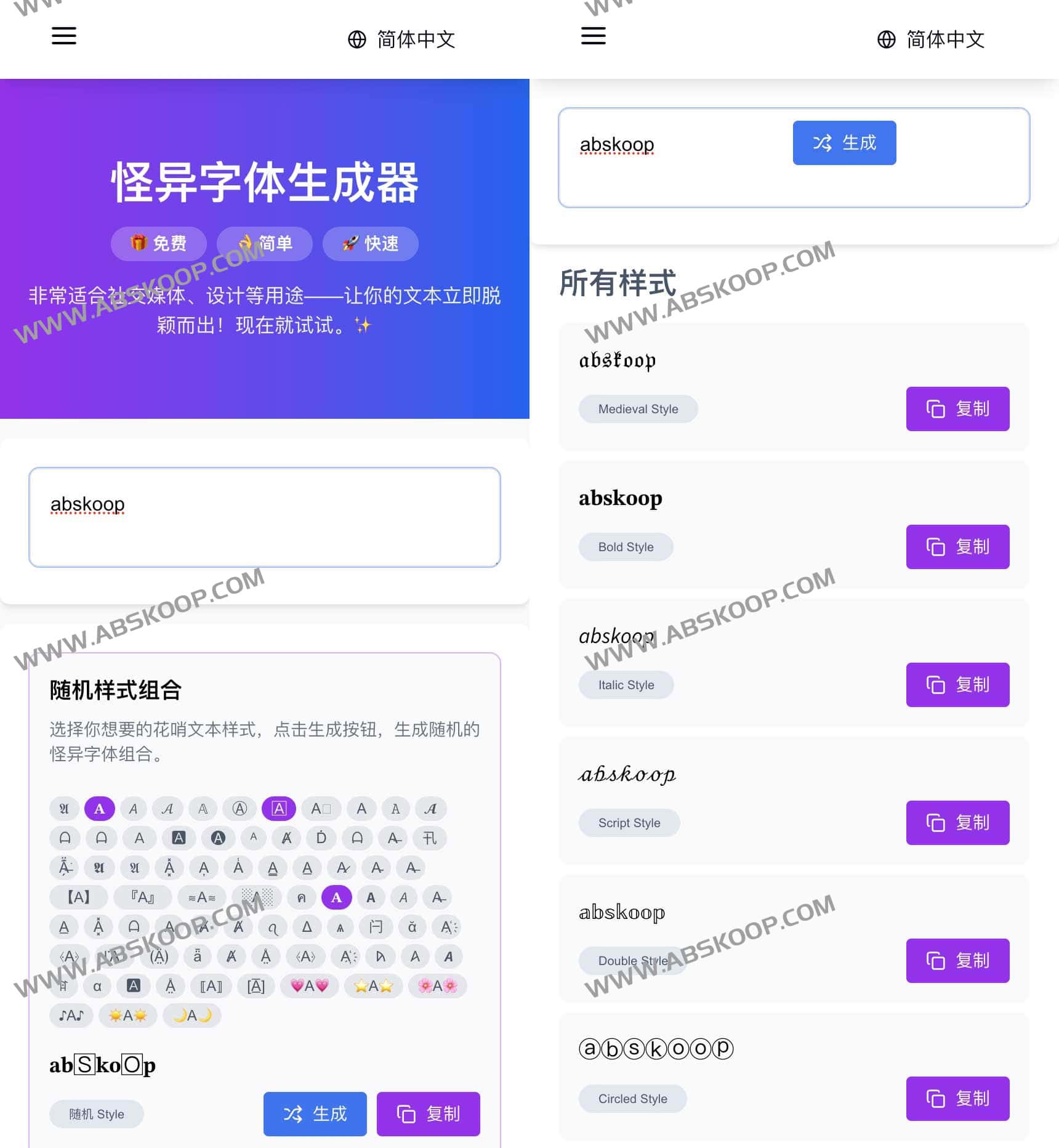
使用怪异字体生成器制作时尚花哨文本的完整步骤
怪异字体生成器:快速打造吸睛的个性化文本
怪异字体生成器 是一款免费的在线文本转换工具,旨在将平庸的文字转化为独特、时尚且极具视觉冲击力的花哨字体。该工具无需复杂的 CSS 设定,通过利用 Unicode 字符集,用户可以将生成的创意文本直接复制并粘贴到各类平台,瞬间提升内容的辨识度与吸引力。
使用怪异字体生成器制作时尚花哨文本的完整步骤
适用场景
由于其强大的兼容性,该工具生成的文本可广泛应用于以下社交媒体和设计场景:
• 社交平台:TikTok、Instagram、Facebook、Twitter (X) 的个人简介或动态。
• 即时通讯:WhatsApp 等聊天软件中的个性化消息。
• 内容创作:YouTube 标题、网站装饰性文本及各类创意设计作品。
操作指南
2. 在输入框中键入需要转换的普通文本。
3. 从内置的 100 多种动态更新的字体风格中选择心仪的样式。
4. 复制生成的怪异字体,直接粘贴至目标平台即可。